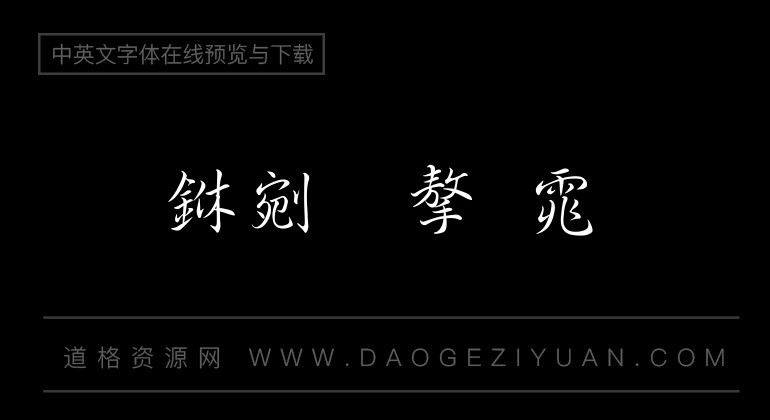
超研泽中行书是一款由超研字体开发的非常优雅的汉字字体,字形设计源于中国传统行书,经过超研字体设计师精心设计,以现代感为主,融合古典传统特色,在保留传统行书特色的同时,也增加了更多的现代感,使字体更加简洁、精致、优雅。超研泽中行书字体可以用于各种印刷、网络、平面及多媒体等多种场合,是一款非常实用的汉字字体。文件名:ChaoYanZeZhongXingShu-2.ttf
超研泽中行书是一款非常不错的手写艺术字体,具有很好的视觉感,适合于文化类的宣传设计、商业类品牌的广告和产品包装设计以及个性化文字排版等较多场景。